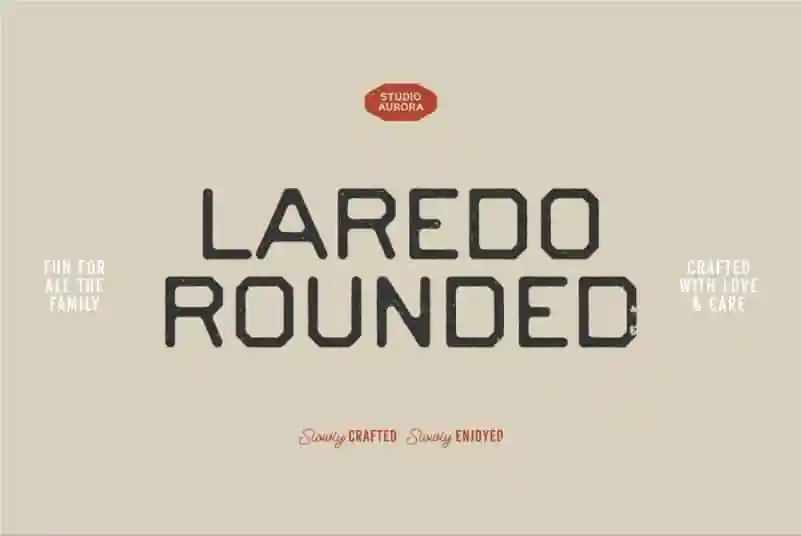
Laredo Display Font – Download Grátis
A Laredo Font é uma fonte grátis inspirada no estilo vintage criada pela Studio Aurora. Sua estética arredondada remete ao universo ruidoso e vibrante do oeste americano, misturado com a cultura customizada dos motociclistas e a toque vintage que torna essa fonte uma escolha versátil. O designer inspirou-se na simpatia dos cavalos, nas motocicletas customizadas em homenagem aos ícones do oeste, e nos anos 50 e 60, período cheio de glamour e sofisticação. Este pacote inclui ilustrações adicionais que a tornam perfeita para logotipos, selos, roupas, cartazes e muito mais. Seja você uma marca fashion ou um estilista gráfico, a Laredo Font certamente se encaixa em seu projeto de design.